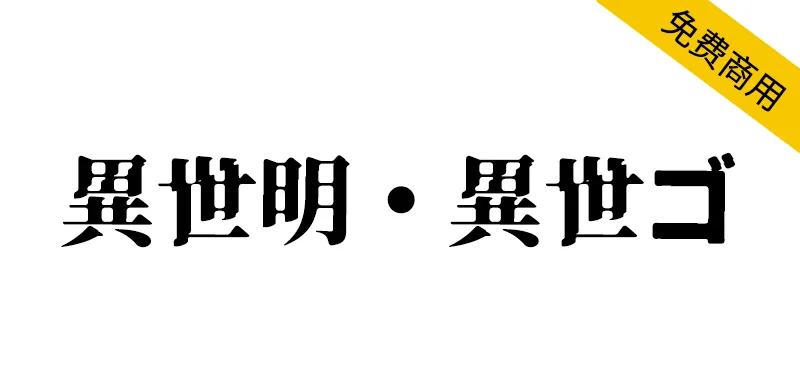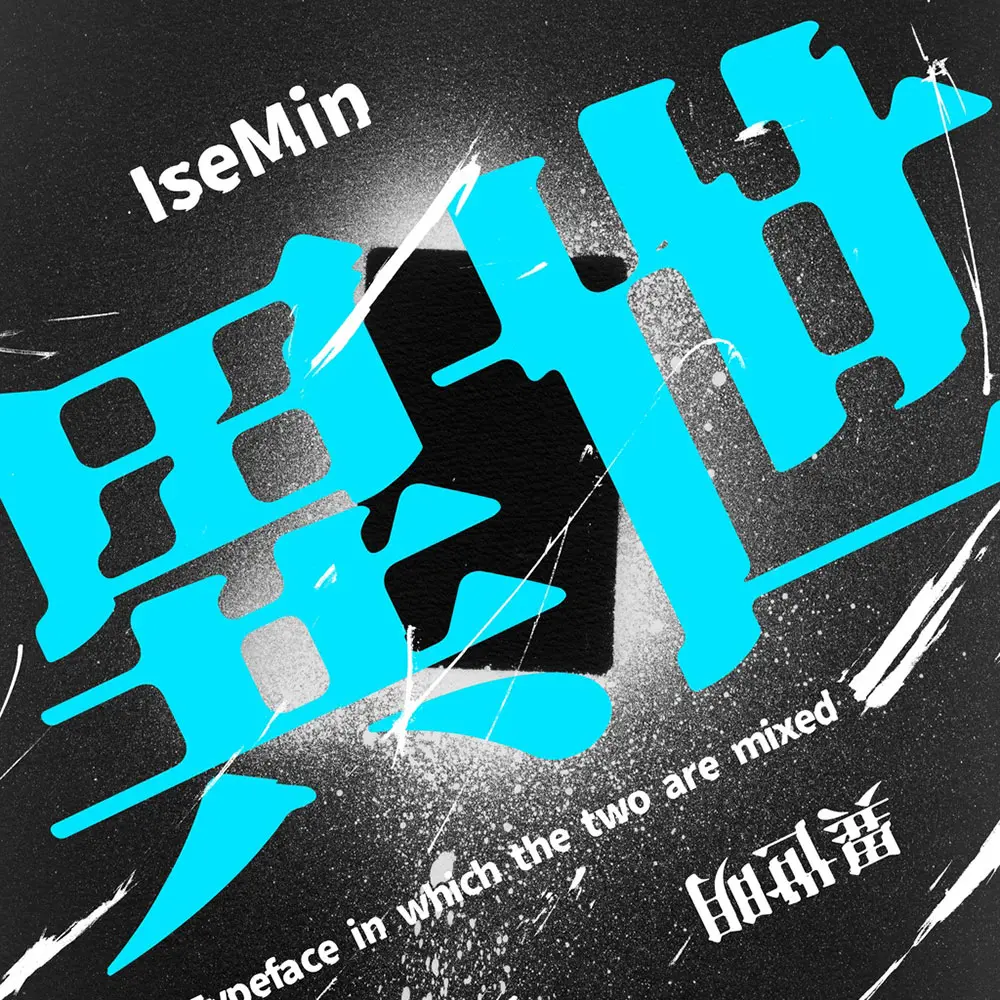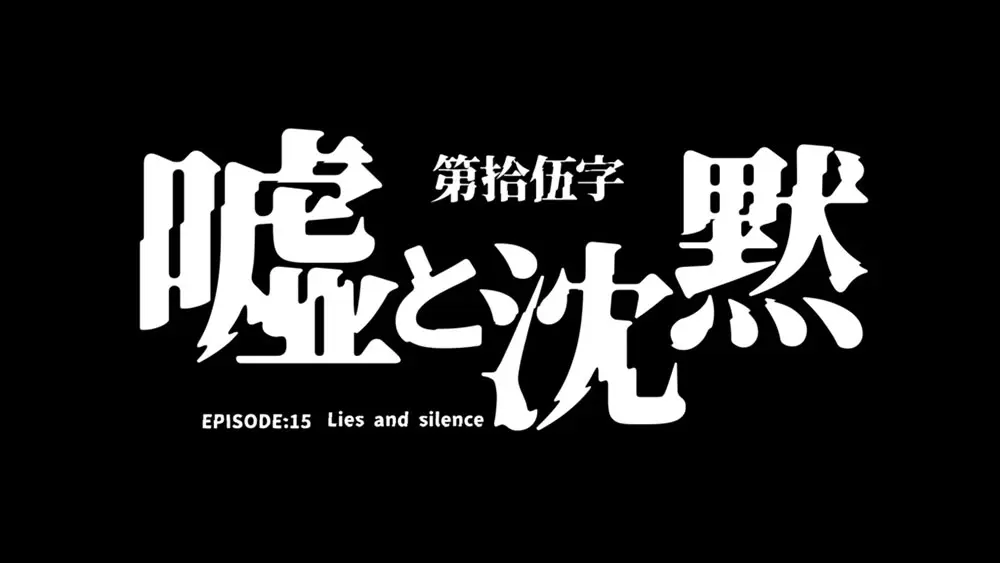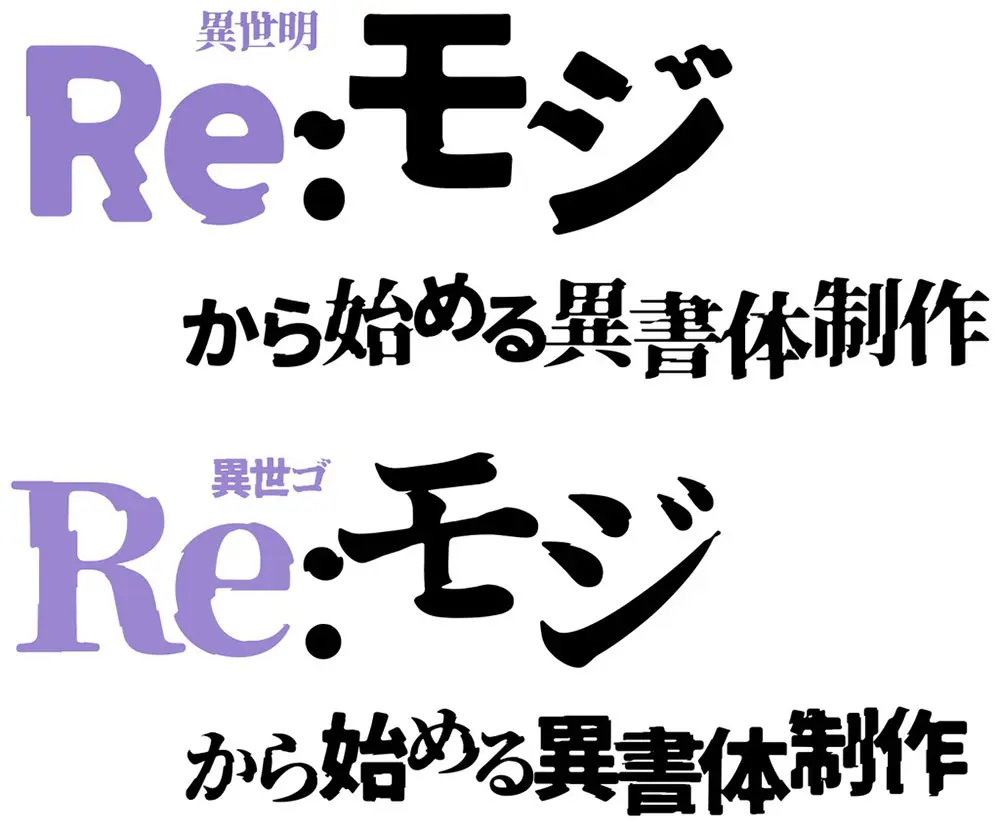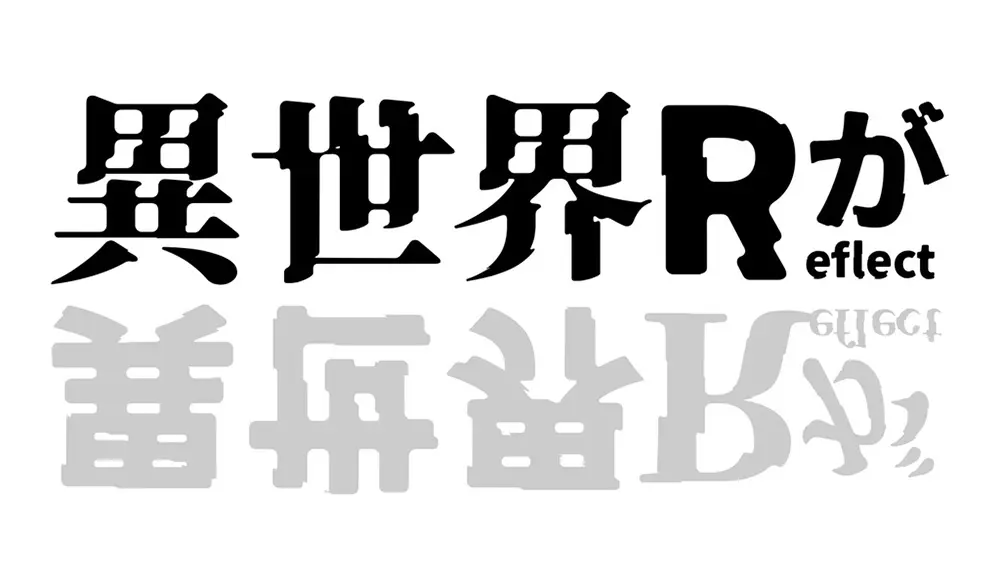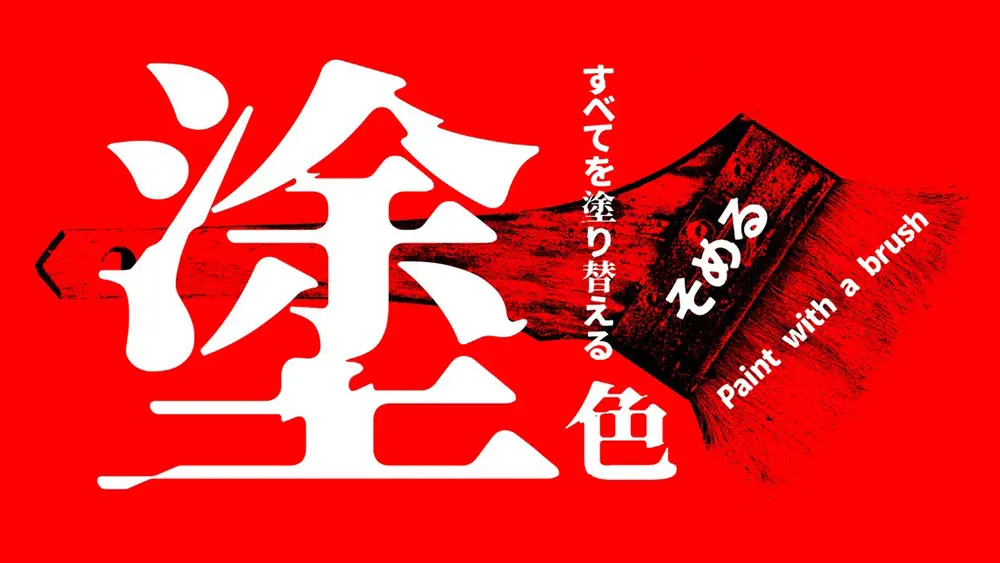
異世明・異世ゴ預覽
異世明・異世ゴ介紹
異世明・異世ゴ是一款將日語版思源宋體進行改造而成的派生字體,“異世明”是漢字是明朝體,其他文字是哥特體的字體。相反,“異世ゴ”的漢字是哥特體,其他文字是明朝體的字體。
字體在向異世界轉移時,“軟綿綿”的世界彷彿扭曲了一般,給人一種崩潰的感覺。非常適合用於特殊的標題、logo字體。
異世明、異世ゴは「源ノ明朝」「源ノ角ゴシック」のフォントを改変して製作した派生フォントです。「異世明」は漢字が明朝體で、その他の文字がゴシック體のフォントです。逆に「異世ゴ」は漢字がゴシック體で、その他の文字が明朝體のフォントです。
異世界に転移(ワープ)するときに「ぐにゃ」っと世界が歪むような崩れた感じのデザインになっています。かなり特殊な見出し・ロゴ向けのフォントに屬すると思います。